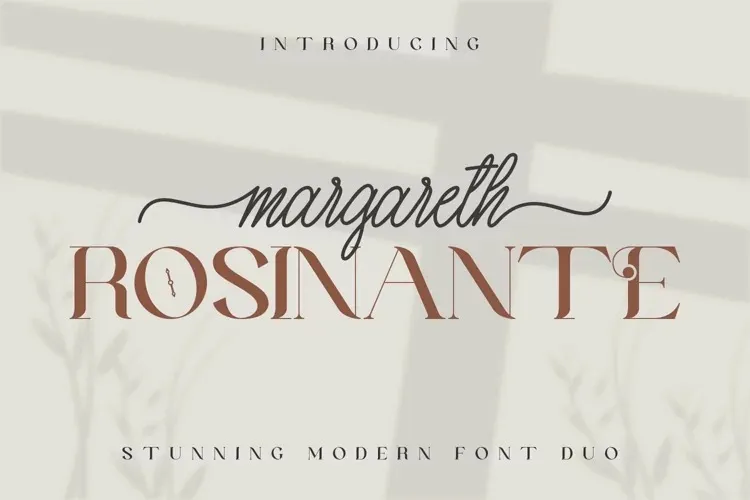
A Margareth Rosinante Font Duo é uma paixão para entusiastas do design gráfico que buscam fusões perfeitas entre serif e script. Esta família de fonts é resultado de um trabalho meticuloso, criando duas faces que se complementam perfeitamente: uma fonte monolinea em rogo e outra serif com uma pitada vintage. As características desta dupla de fonts combinam elegância e sofisticação, refletindo a consistência entre o estilo serif e o script. A grande diferença entre estas duas formas cria um contraste impressionante que torna este conjunto perfeito para qualquer design. Seja em materiais impressos ou digitais, a Margareth Rosinante Font Duo é ideal para quem busca uma fusão de estilo elegante com um toque clássico e moderno. Esta font será definitivamente um ponto de encontro de alta qualidade entre serif e script, projetada especificamente para comparações exibidas em proporções impecáveis.